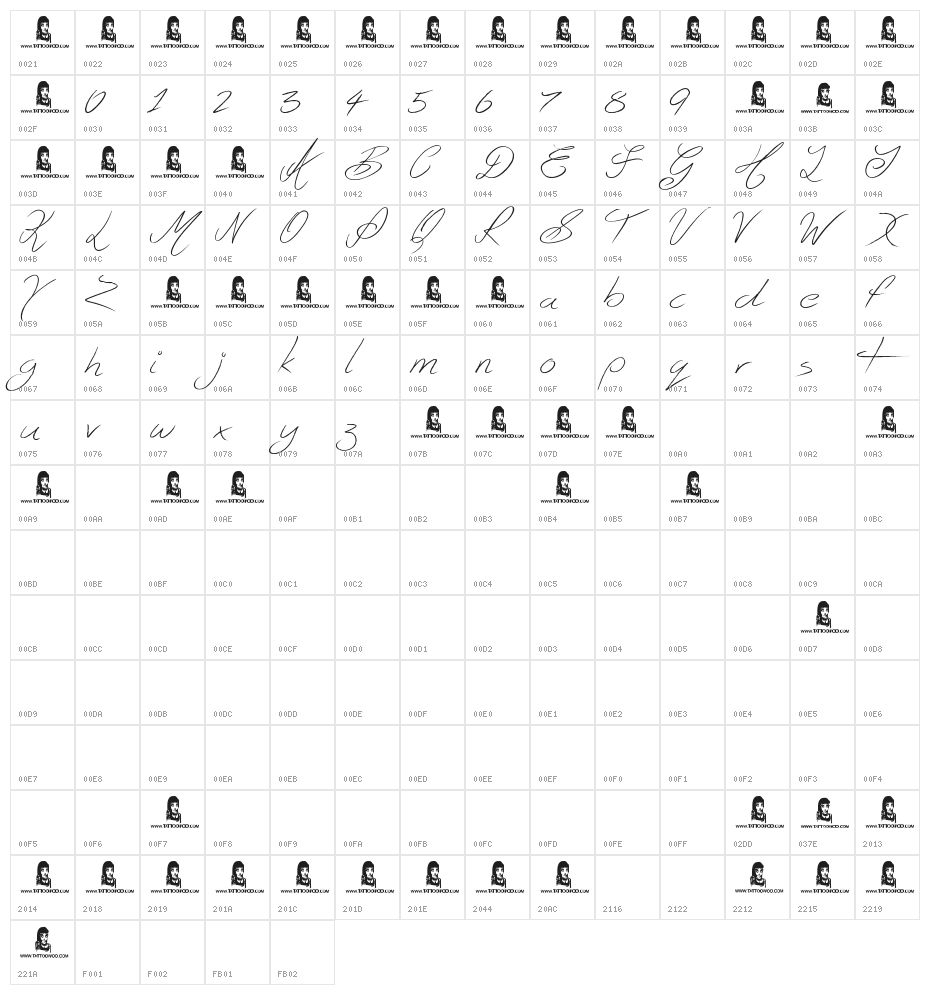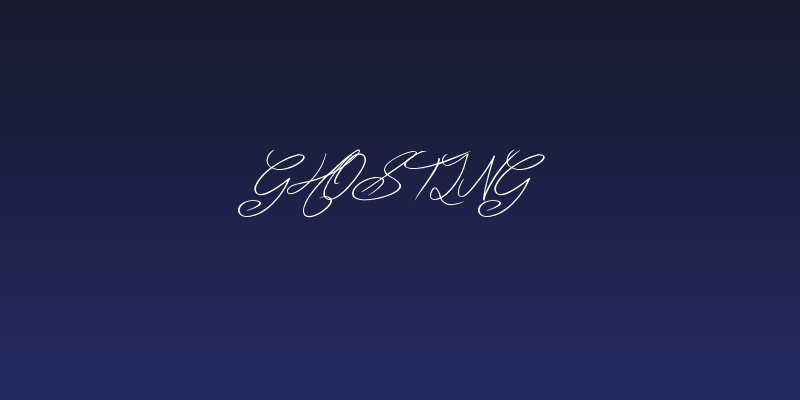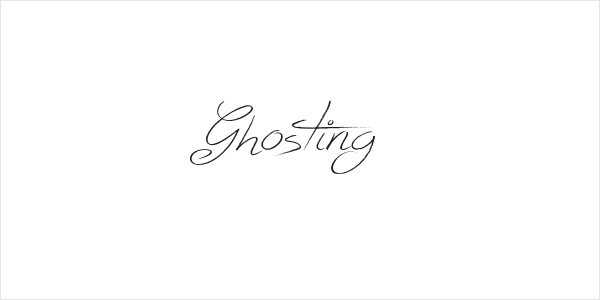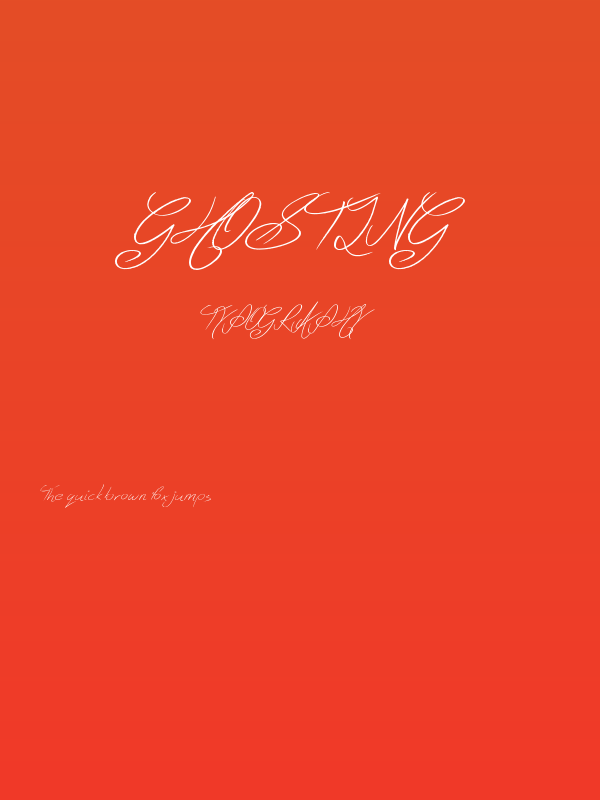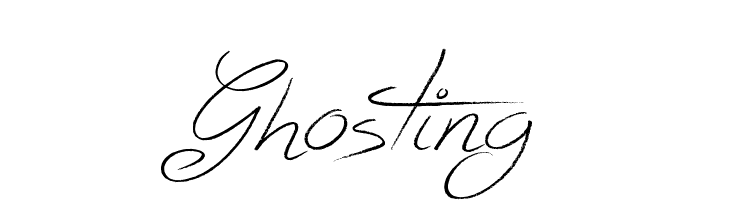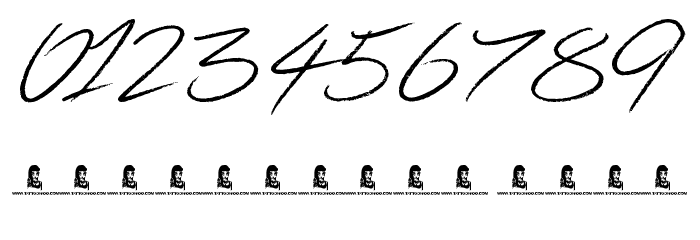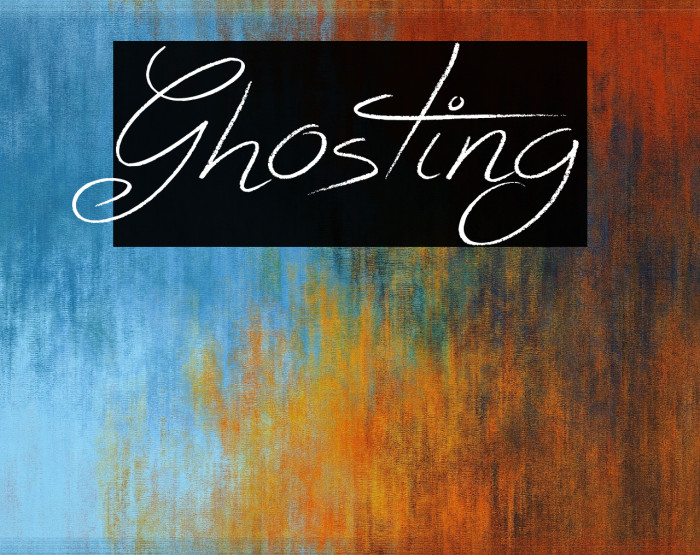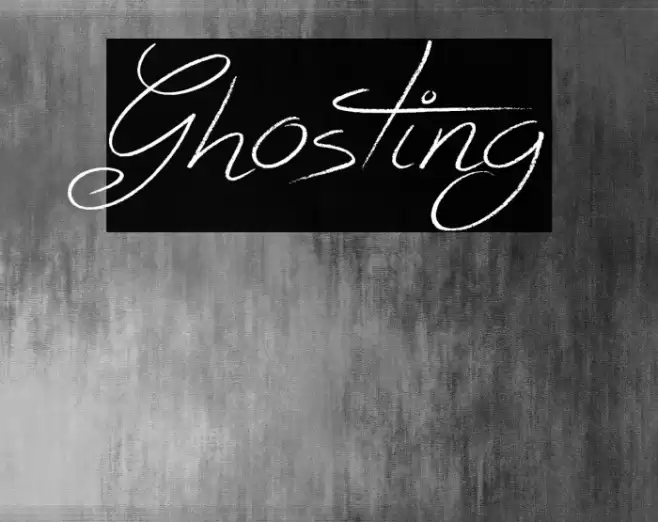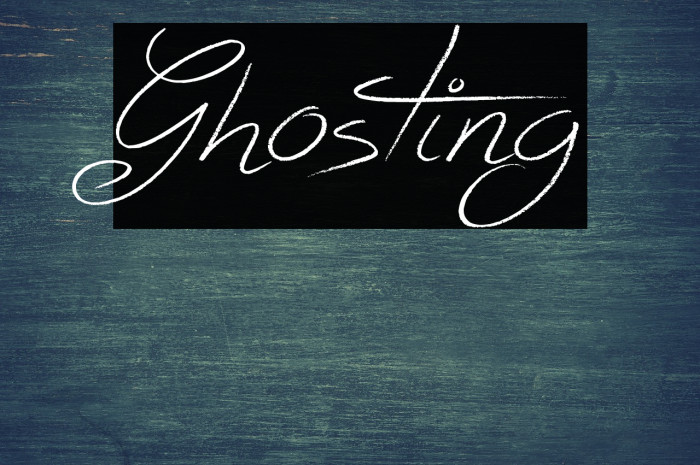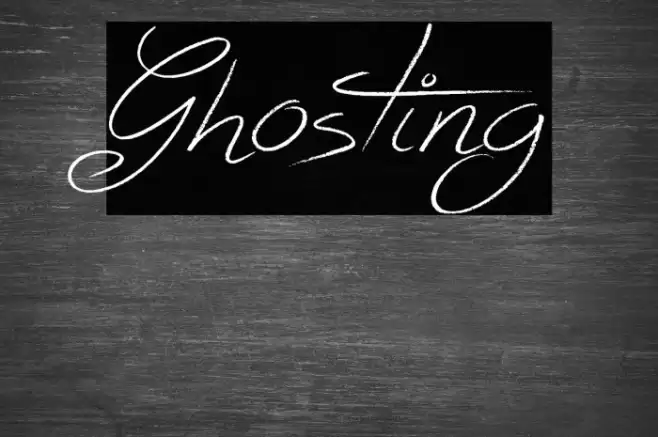
Ghosting Font
| مائل | Yes |
| النمط العام | Elegant, Artistic |
| حالة الاستخدام | Logos, Invitations, Greeting Cards |
| مشاريع مقترحة | Ideal for wedding invitations, greeting cards, personal branding, and elegant logo designs. |